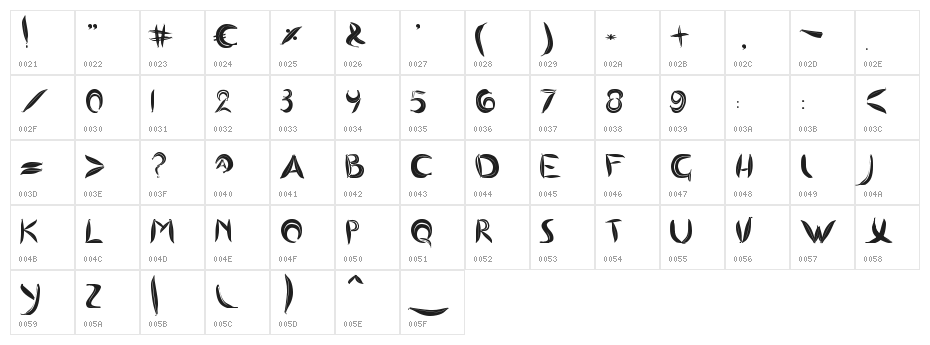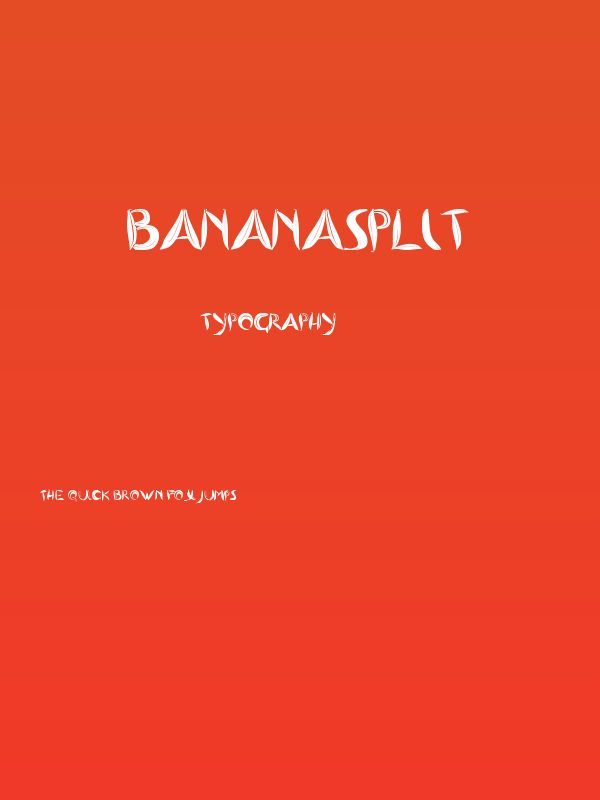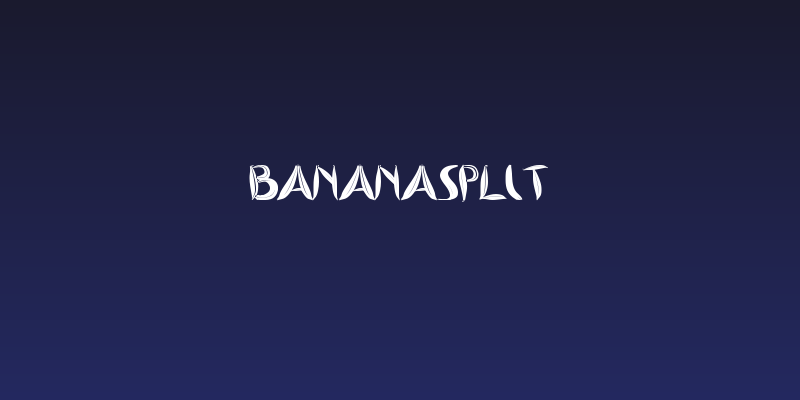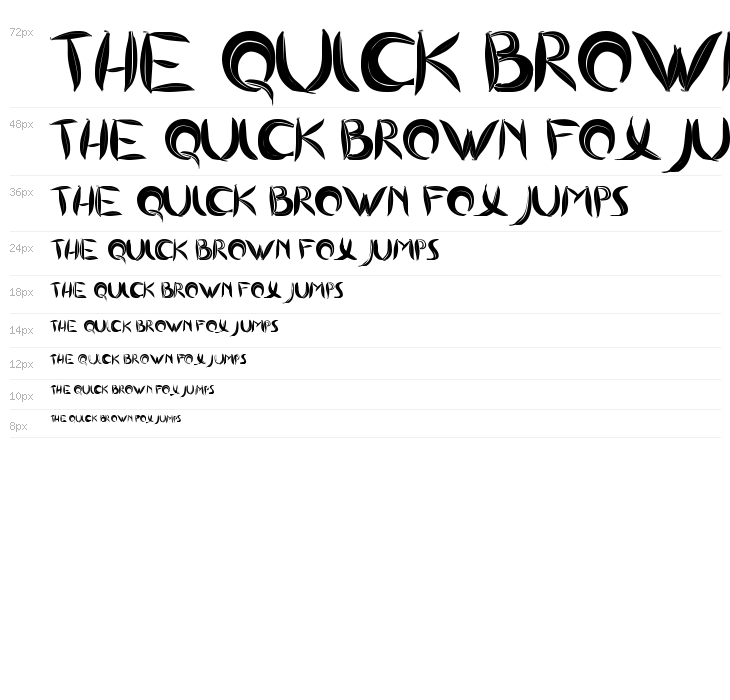
BANANASPLIT Font
| समग्र शैली | Artistic, Organic |
| उपयोग का मामला | Logos, Posters, Creative Headlines |
| सुझाए गए प्रोजेक्ट | Ideal for nature-themed designs, artistic posters, branding for eco-friendly products, or any project needing a creative touch. |